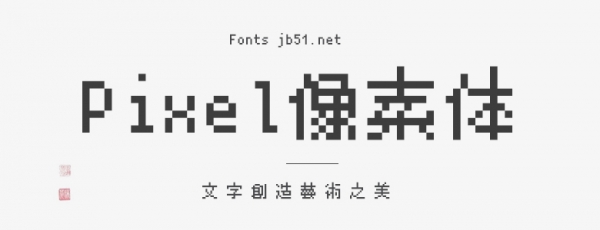
這是一種 TrueType 輪廓字體,看起來像 8 位 Famicom 位圖字體。
特征
TrueType 字體看起來像位圖字體,但只有輪廓。 沒有嵌入位圖。包括粗體。
包含 JIS 1 級(jí)和 2 級(jí)的所有漢字。還包括 ISO-8859-1 (Latin-1) 字符。 添加了一些其他符號(hào)。
它實(shí)際上只是一個(gè) TrueType 等寬字體。它還可以與文本編輯器一起使用。
有兩種類型的字體:PixelMplus12 和 PixelMplus10。 區(qū)別在于原始位圖字體是 12 像素還是 10 像素。